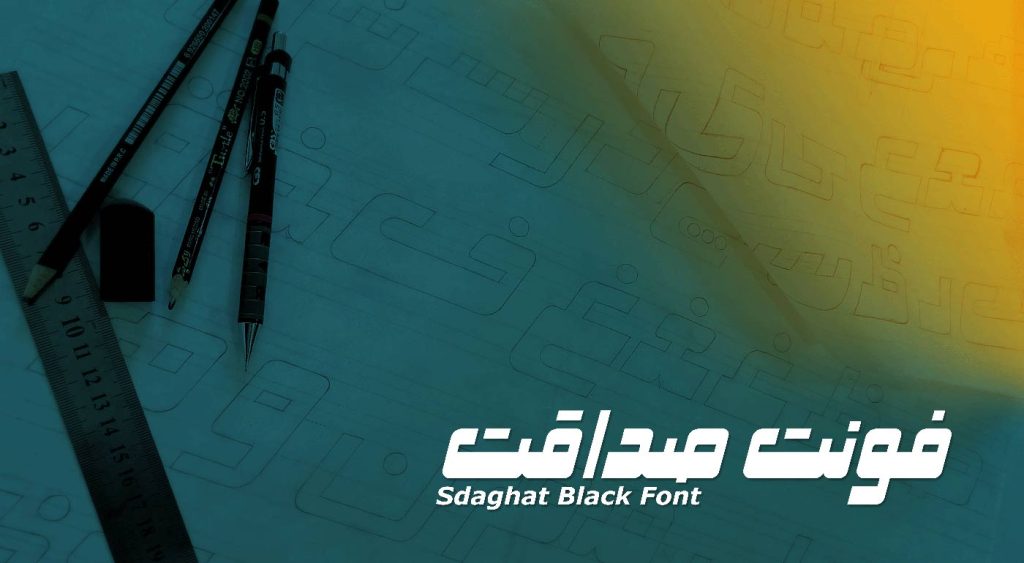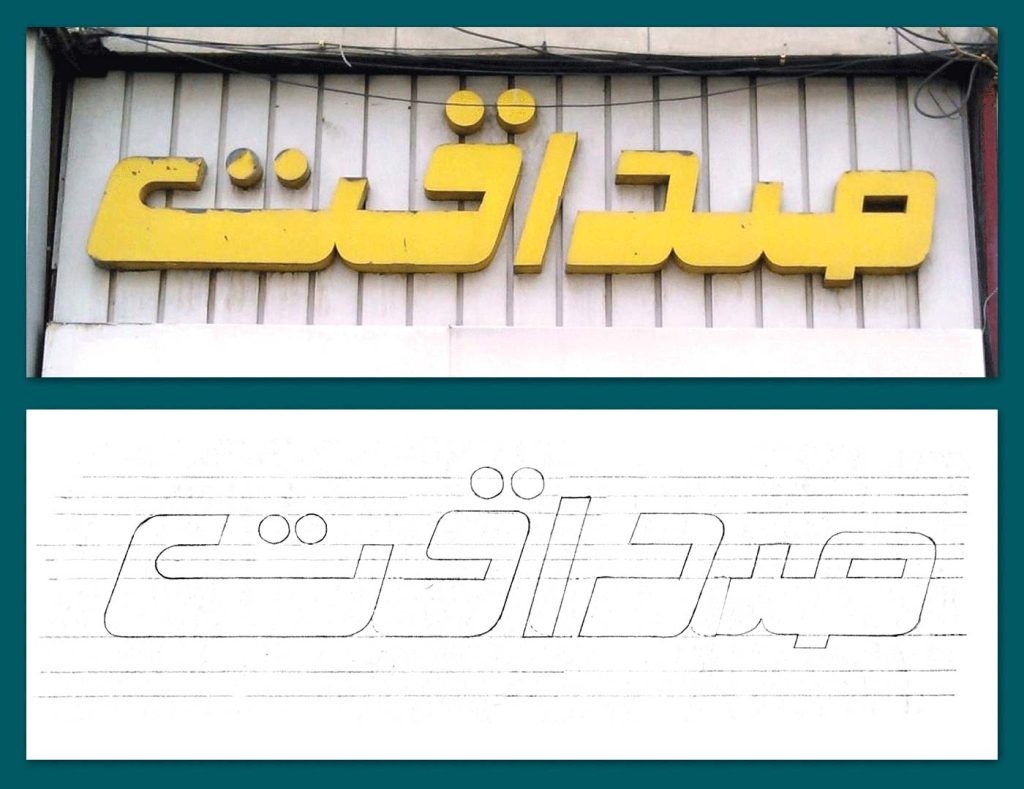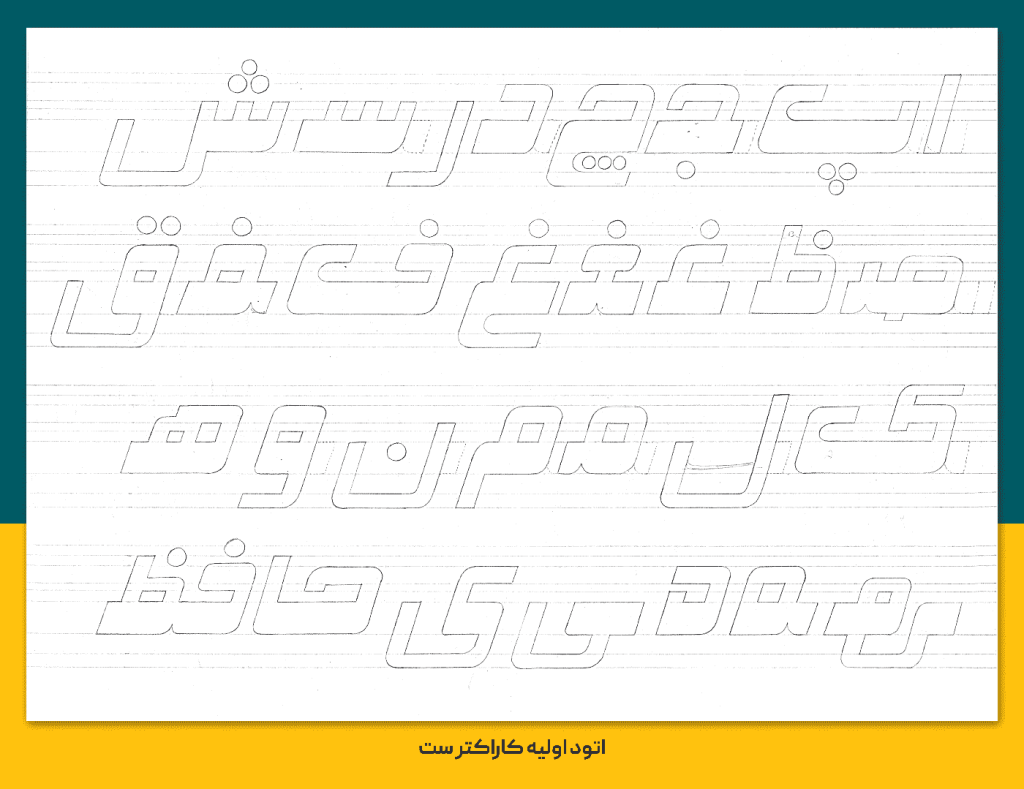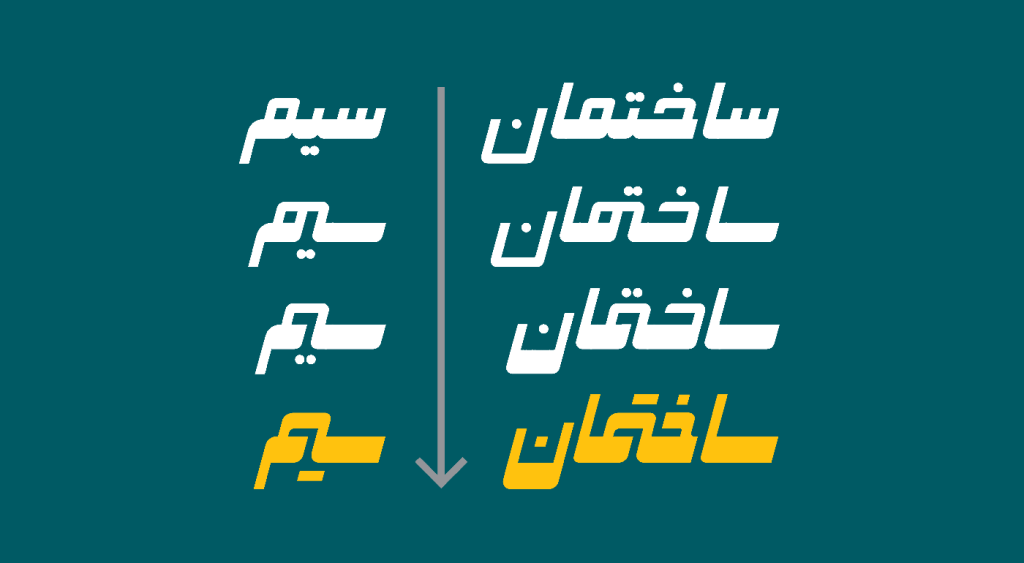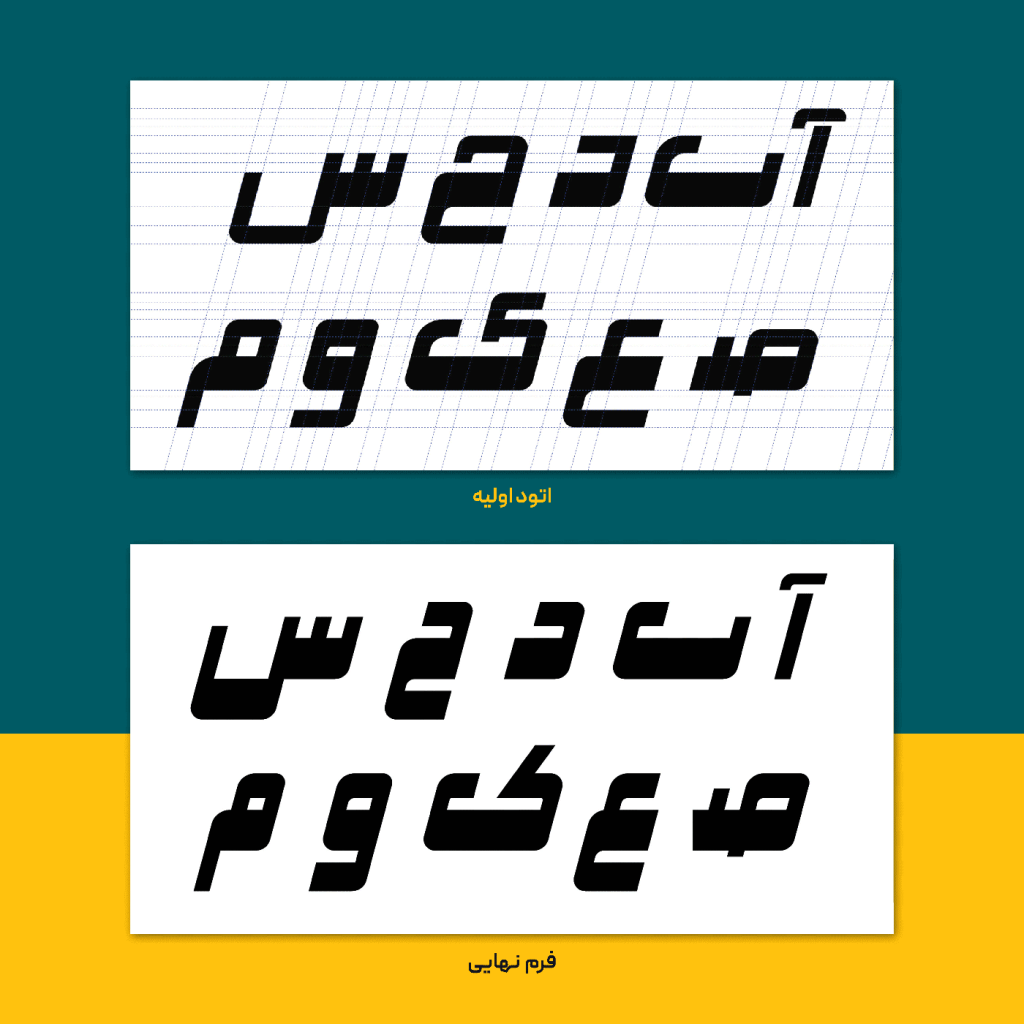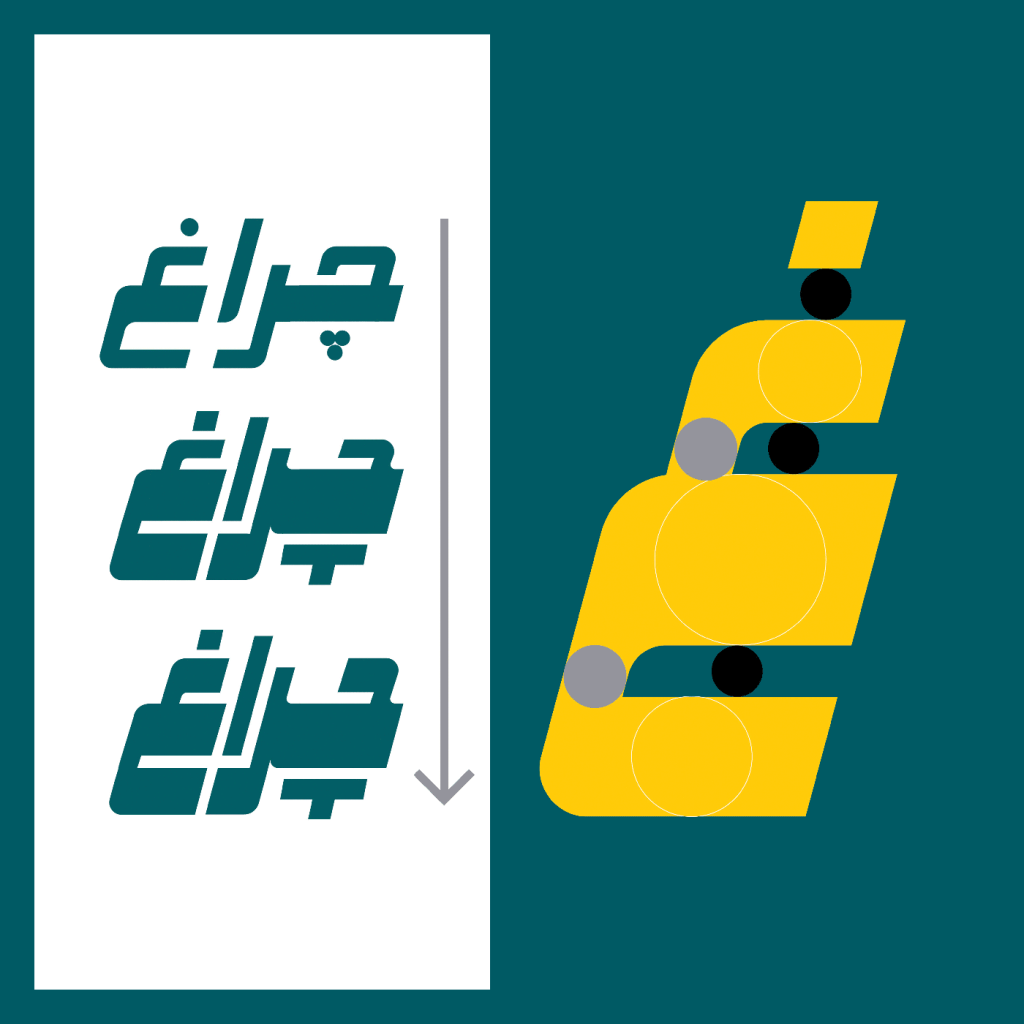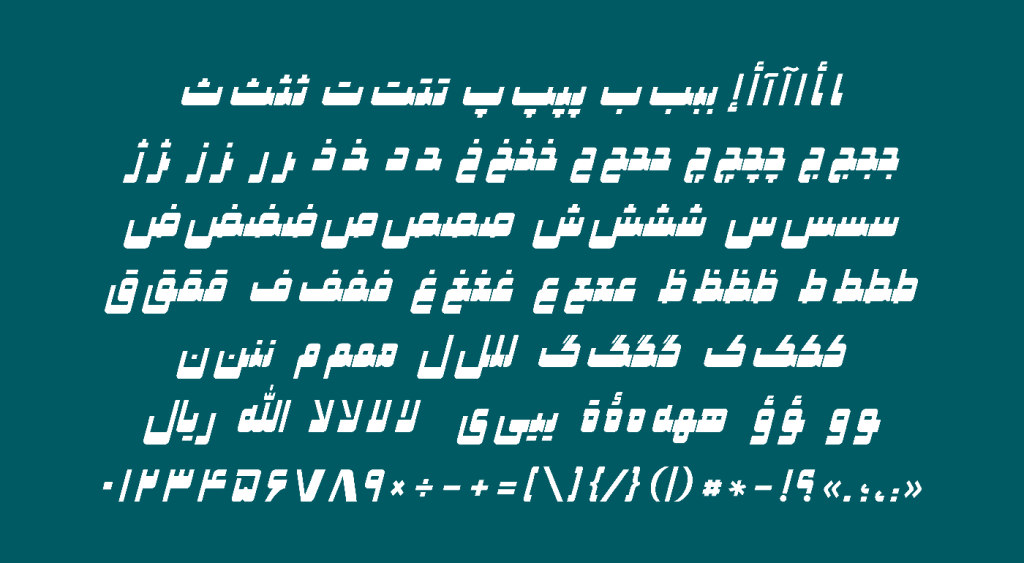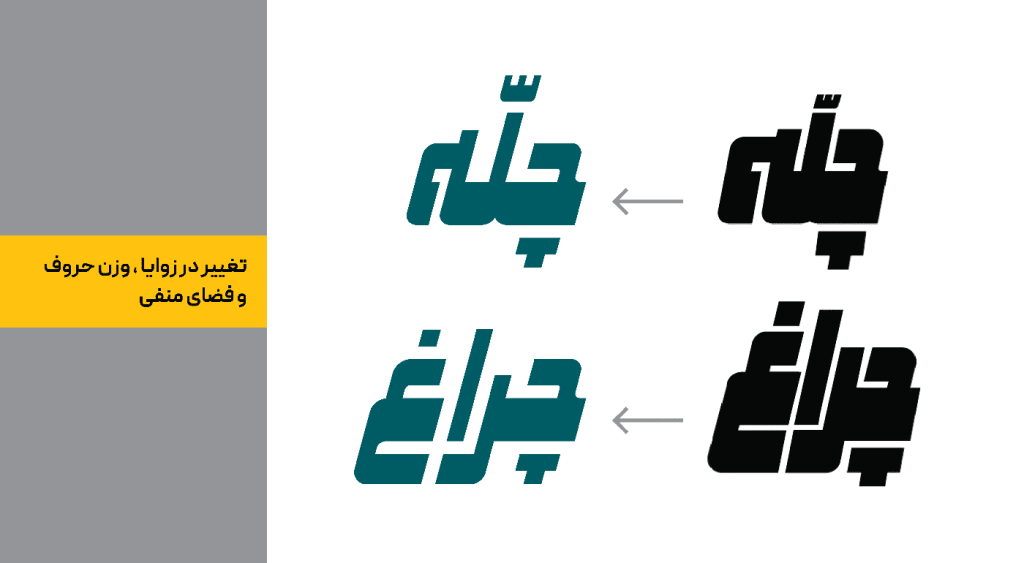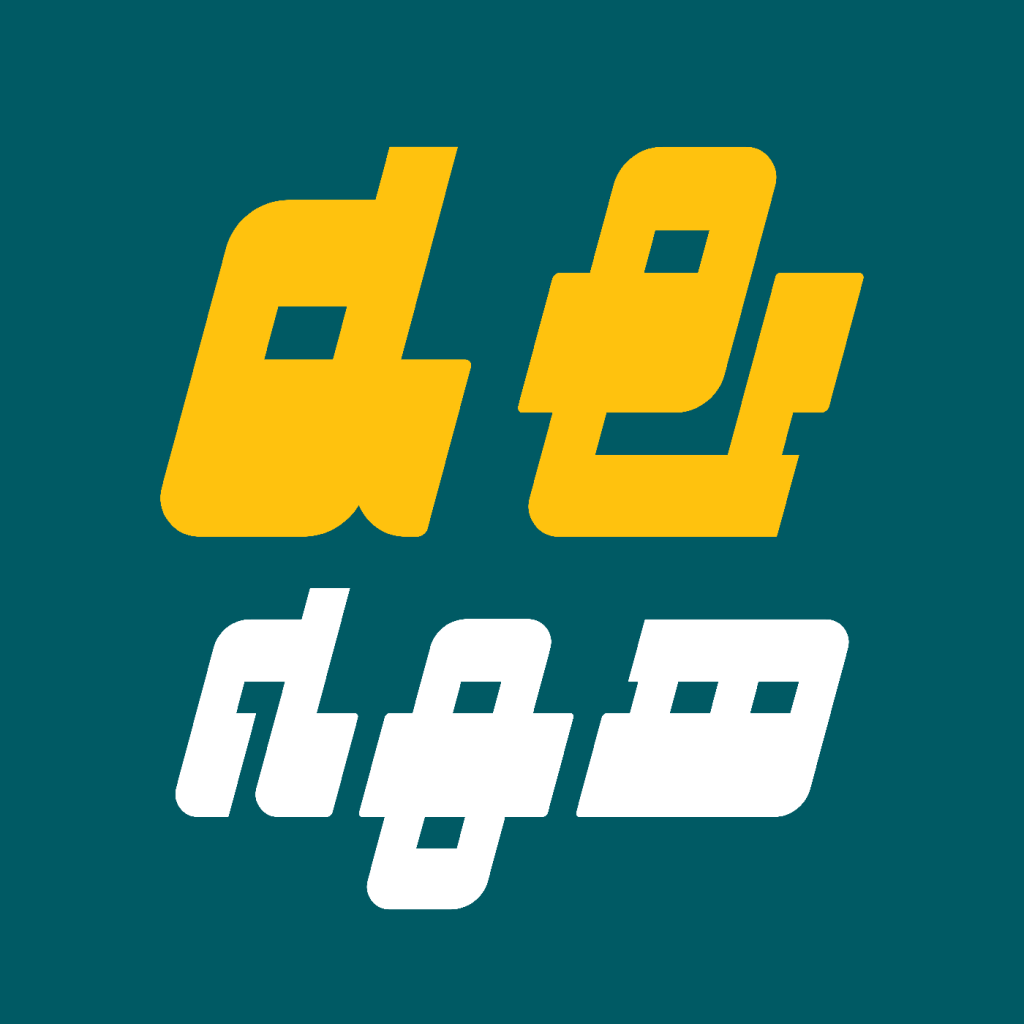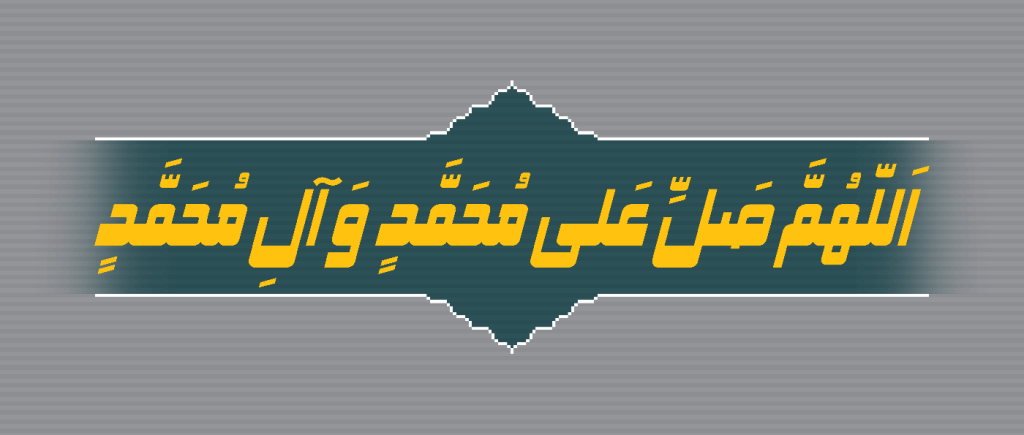
فونت صداقت
فونت صداقت به همت و تلاش آقای احمد رضا رحیمی در یک دوره آموزشی فشرده زیر نظر احسان جعفرپیشه طراحی و پس از آن توسط امین عابدی به فونت تبدیل شده است.
ایده ابتدایی این قلم از یک تابلوی قدیمی حروف برجسته که به همین نام بوده گرفته شده و سپس بررسی فرم حروف موجود و طراحی بقیه حروف بر مبنای بیس اصلی، اتودهای اولیه آماده شد ؛ با چندین مرحله تغییرات در فرم حروف ، زوایا ، ضخامت ها ، سواد و بیاض ها و نقطه ها تایپ فیسی مدرن با حال و هوای تایپوگرافی های قدیمی طراحی شد . این تایپ فیس قابل استفاده در فضای پوستر ، طراحی لوگو، طراحی عنوان و تیتر ، تابلوسازی و … میباشد.
در فونت صداقت برای رسیدن به حالت های مختلف حروف مانند ح و ع لبه دار و ک / ب / ف کشیده یا لبه دار و همچنین استفاده از ترکیب های جدید مانند اتصال دندانه افراشته ص / س / ب / ن / ی به حروف ر / ن / م / ی باید از ترکیب شیفت و همزه برای انتهای کلمه یا حروف جدا و از همزه برای بین حروف استفاده کنید.
طراح در چند مرحله وزن حروف، زاویه ها ، نسبت سفیدی و سیاهی و نقطهها تغییر داده است تا به بهترین نتیجه دست یابد. در تصاویر زیر شما ساختار و شکل این قلم را می بینید
این فونت فقط حاوی حروف فارسی و عربی است.